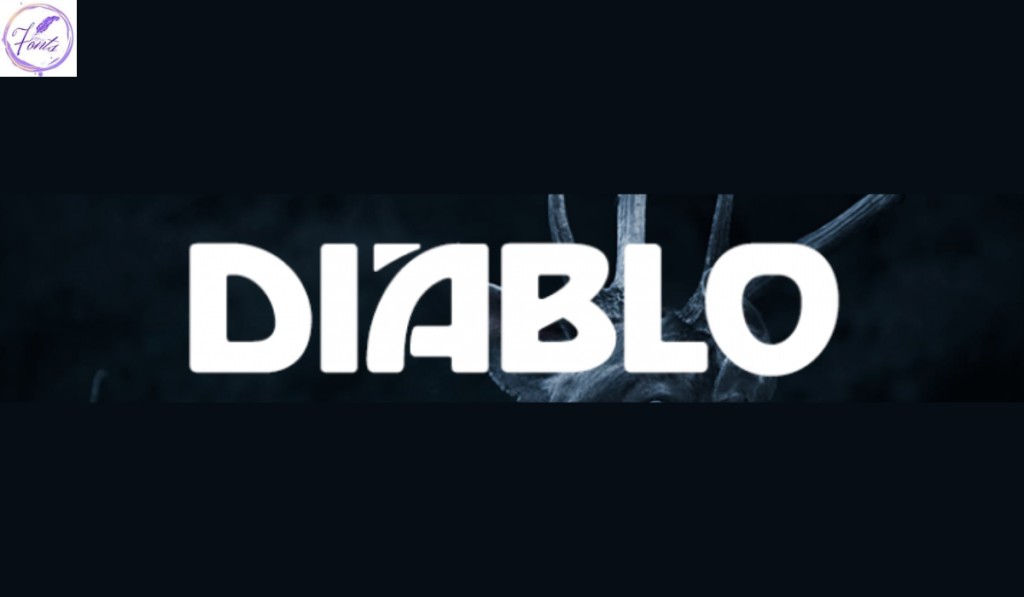
Tác giả: UR Type Foundry
Ngày phát hành: 2014
Ngôn ngữ: Tiếng Việt, Tiếng Anh, và nhiều ngôn ngữ khác
Bộ Font: Diablo
Phân loại: Cá tính, độc đáo
Kiểu chữ: Kiểu chữ không chân
Diablo font là một font chữ độc đáo, lấy cảm hứng từ tựa game nổi tiếng Diablo. Được thiết kế bởi người hâm mộ tên là UR Type Foundry với niềm đam mê mãnh liệt vào năm 2014, font này mang đậm chất kỳ bí và cổ điển, rất phù hợp cho các thiết kế liên quan đến game, phim ảnh hoặc các dự án cần sự huyền bí. Với các đường nét đậm, rõ ràng, diablo font mang đến sự mạnh mẽ và đầy sức hút cho bất kỳ tác phẩm nào.
Đánh giá diablo font
Diablo font nhận được nhiều đánh giá tích cực từ cộng đồng thiết kế nhờ vào tính thẩm mỹ và sự linh hoạt trong ứng dụng. Các nhà thiết kế yêu thích font này vì nó dễ đọc, dễ sử dụng và mang lại cảm giác mạnh mẽ, kỳ bí. Ngoài ra, diablo font còn hỗ trợ đầy đủ tiếng Việt, giúp bạn dễ dàng tạo ra những thiết kế đậm chất riêng và nổi bật. Sự kết hợp giữa phong cách cổ điển và hiện đại làm cho diablo font trở thành lựa chọn tuyệt vời cho nhiều dự án khác nhau.